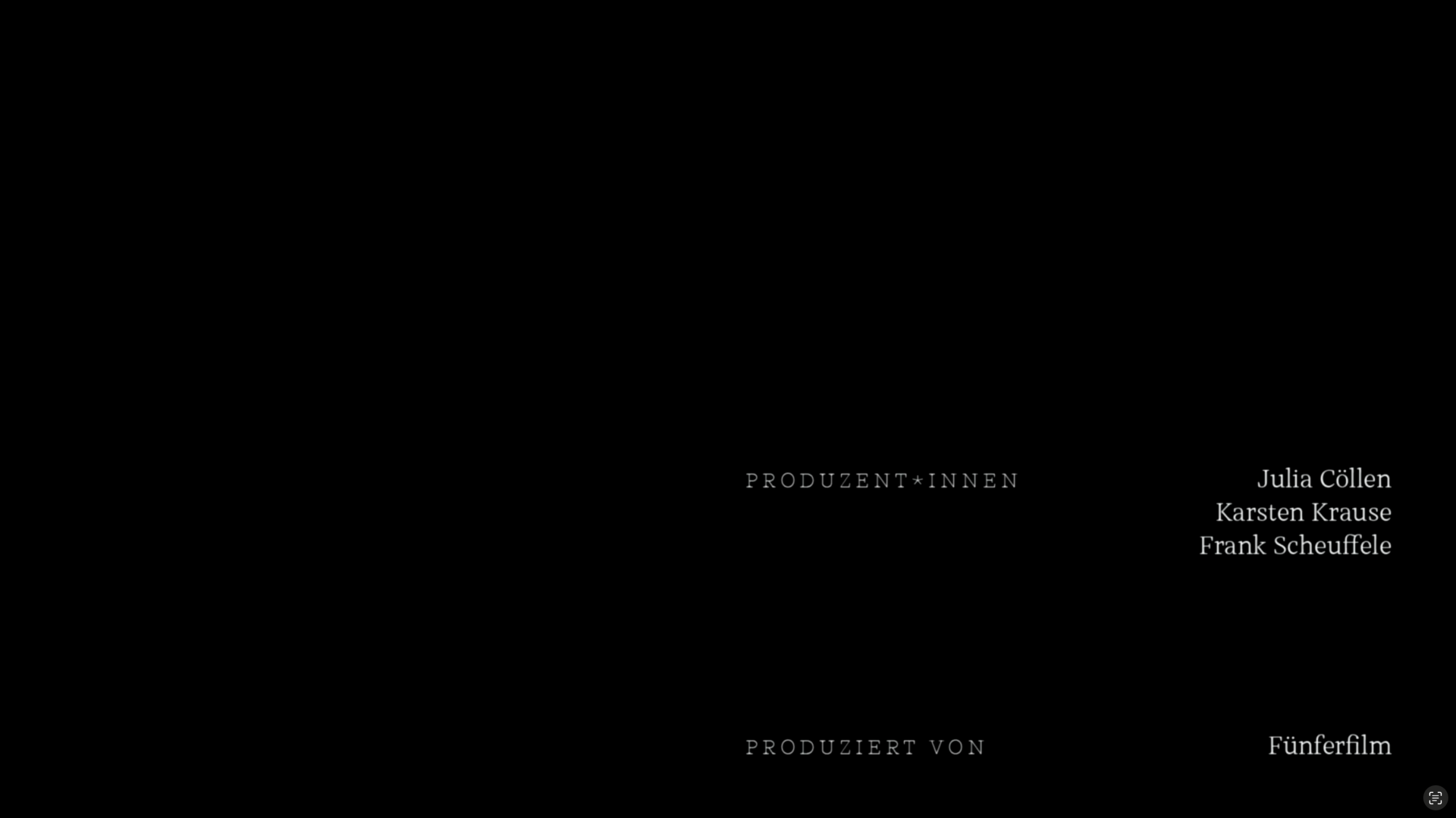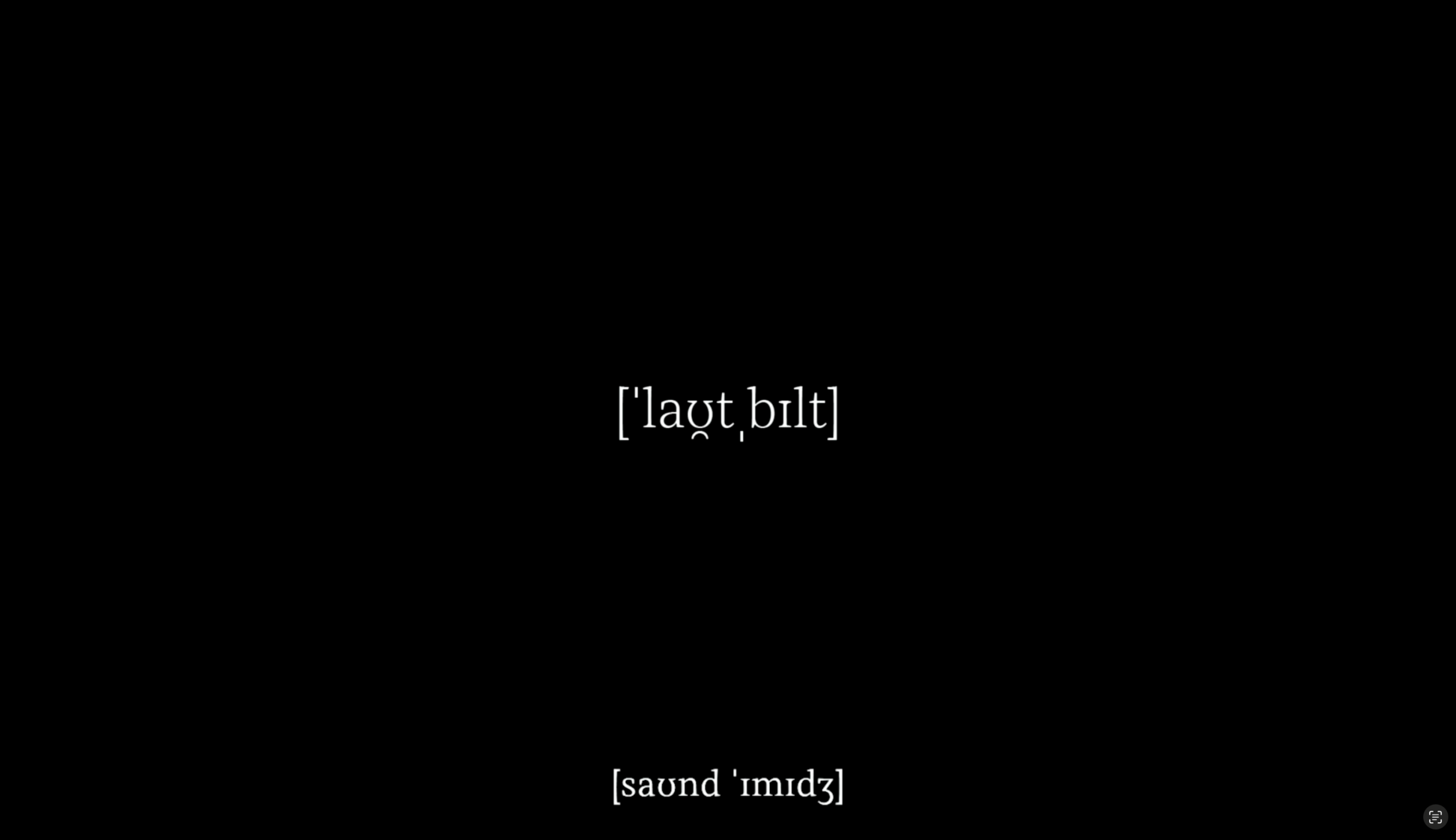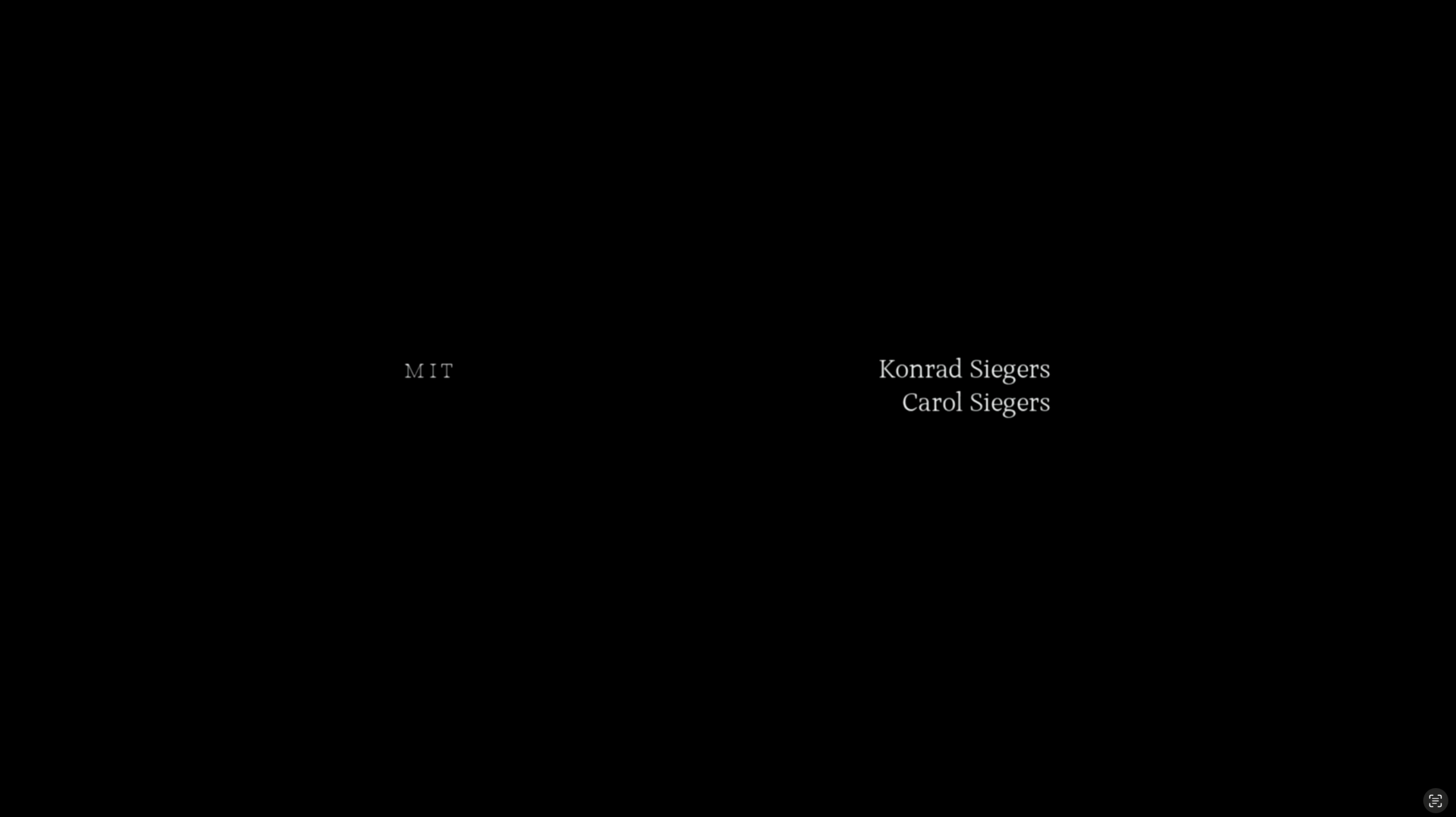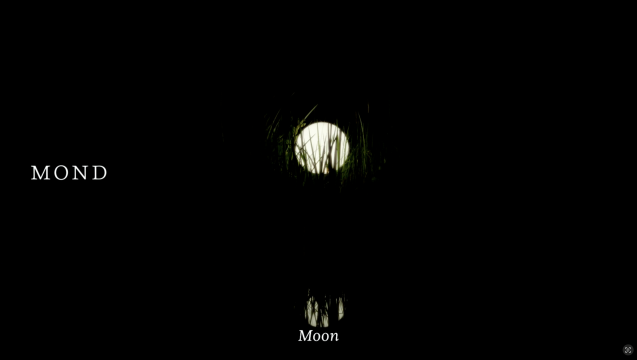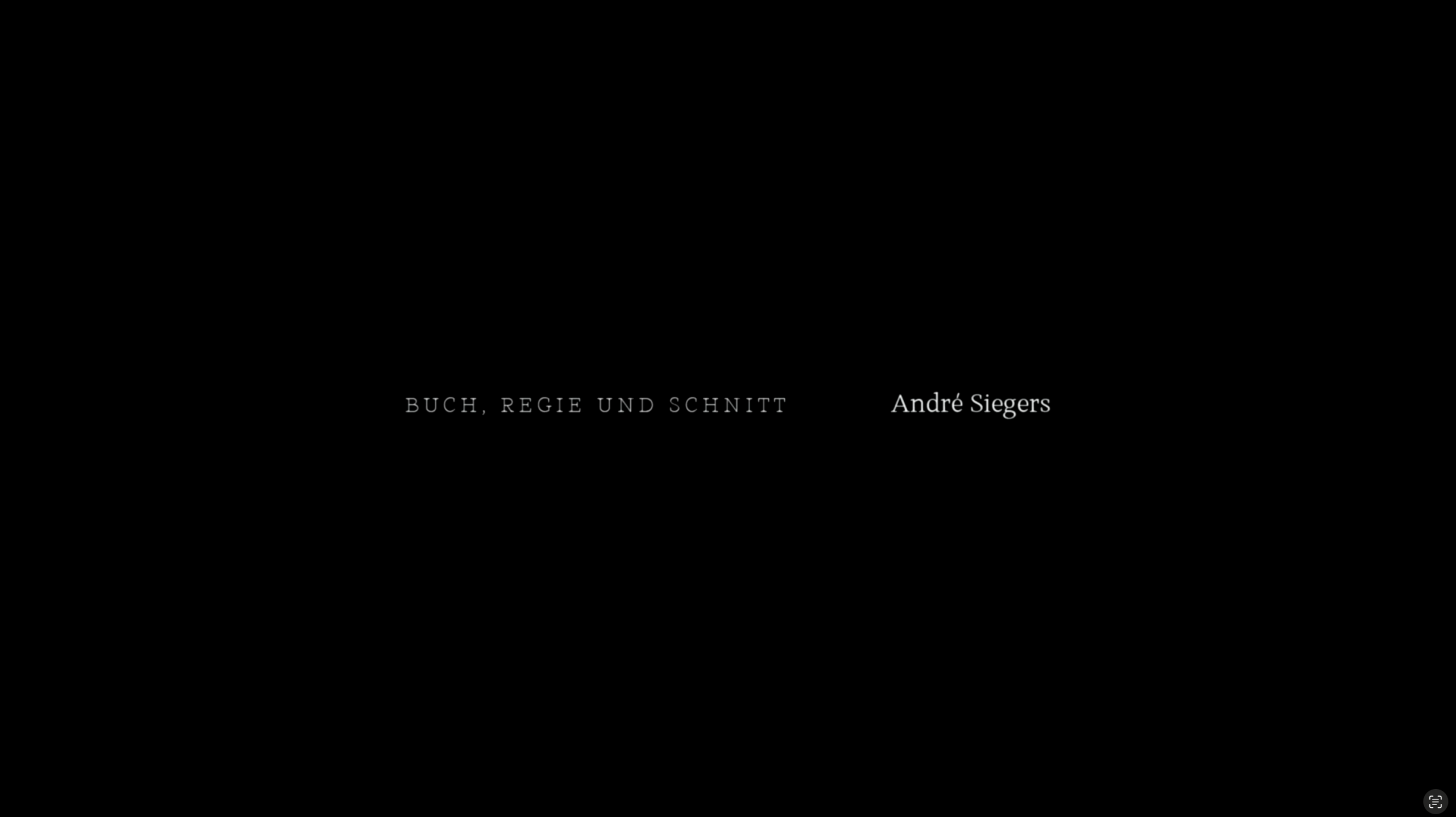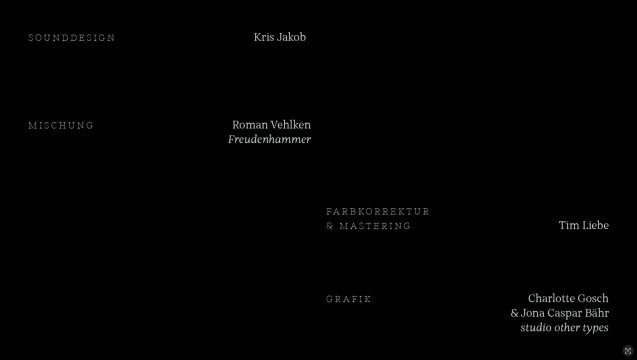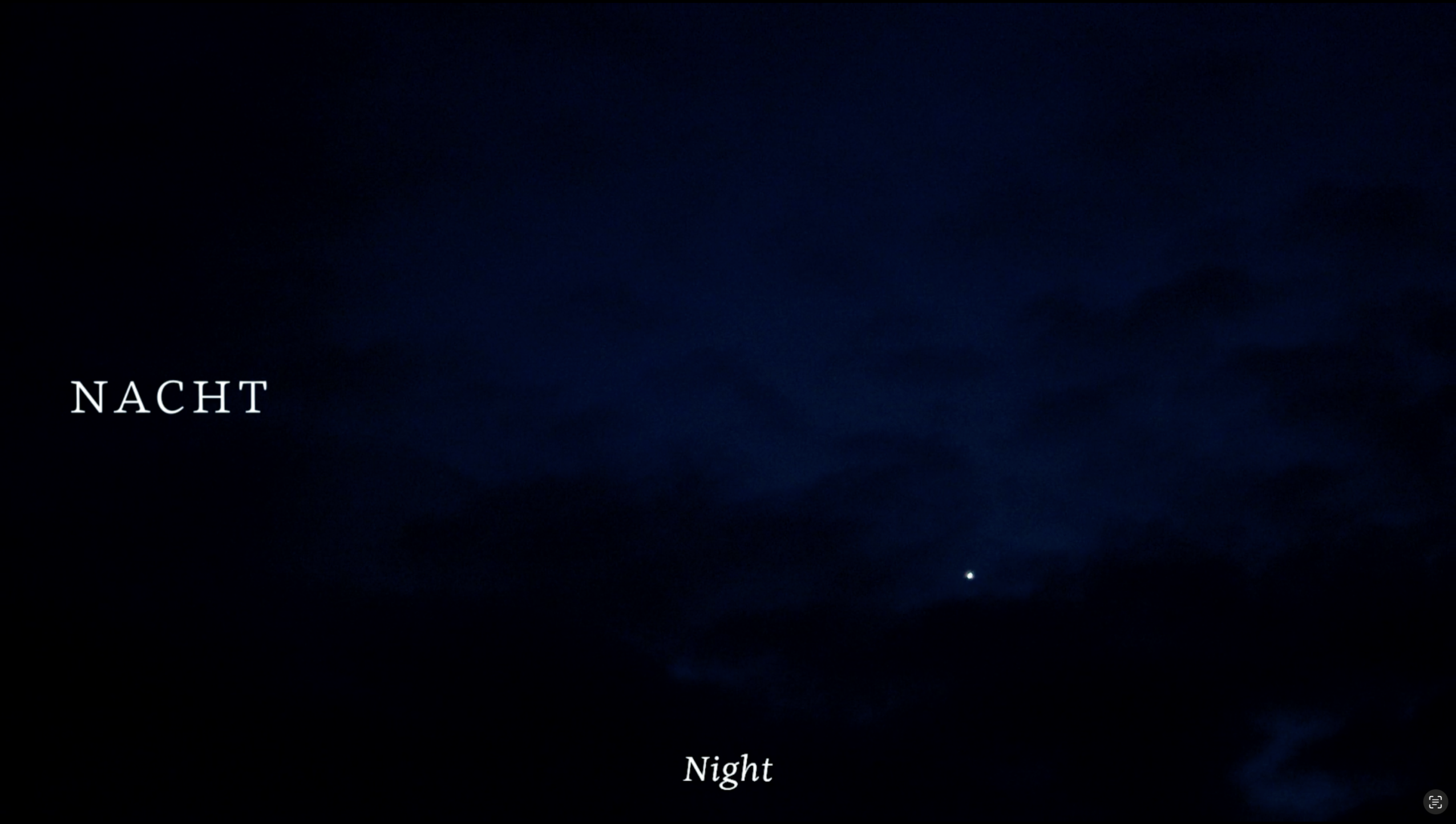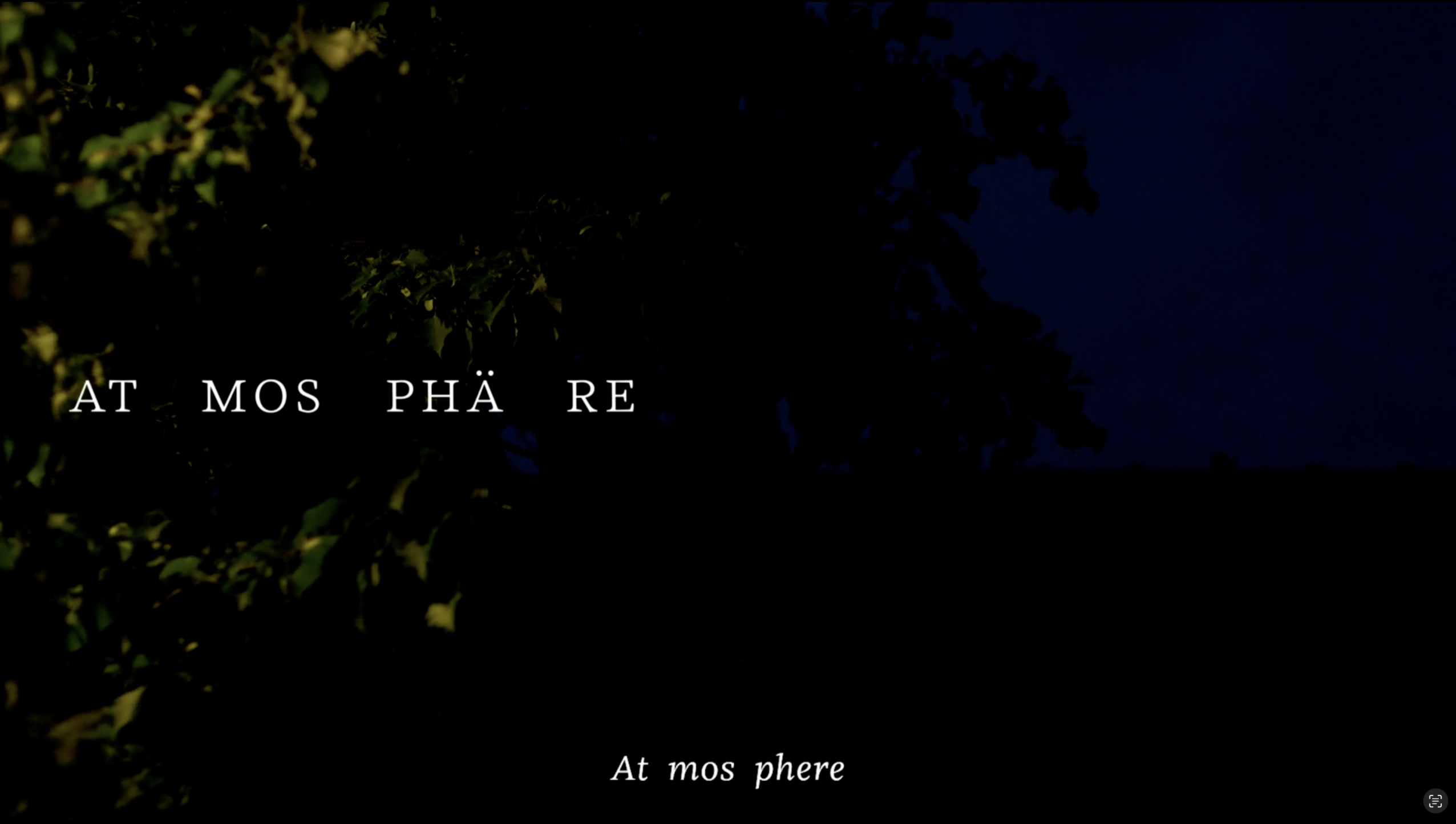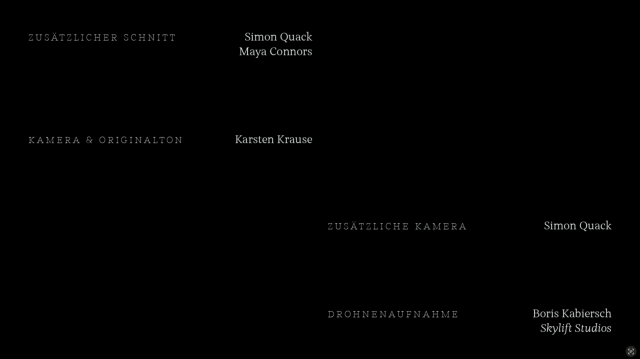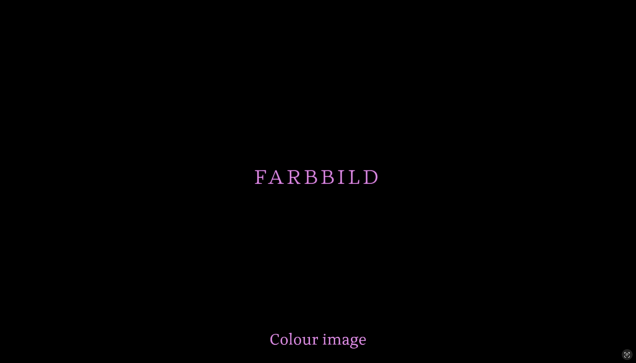
Im Kurzfilm Die Stimme des Ingenieurs von André Siegers absolviert Konrad Siegers sein Artikulationstraining. Siegers’ Muskeln zucken kaum merklich, er ringt mit den Worten. In repetitiven Übungen setzt er sich dem Fortschreiten seiner Krankheit entgegen. Das wohlorganisierte Eigenheim, eine weitere Stütze wider den Kontrollverlust. Seine Stimme soll in einem Sprachprogramm konserviert werden, das ist dem Vater wichtig. Aus dem Kassettenspieler singt ihr Echo, der Klang der Zukunft ist elektronisch.
Die Titelgestaltung greift den Verlust von Sprache und Stimme sowie die Endlichkeit des Seins durch Lautschrift und Silbentrennungen auf, die die Sprachübungen des Protagonisten verbildlichen und das Leseverhalten der Zuschauer bestimmen.
Schrift: Kaius von TypeMates